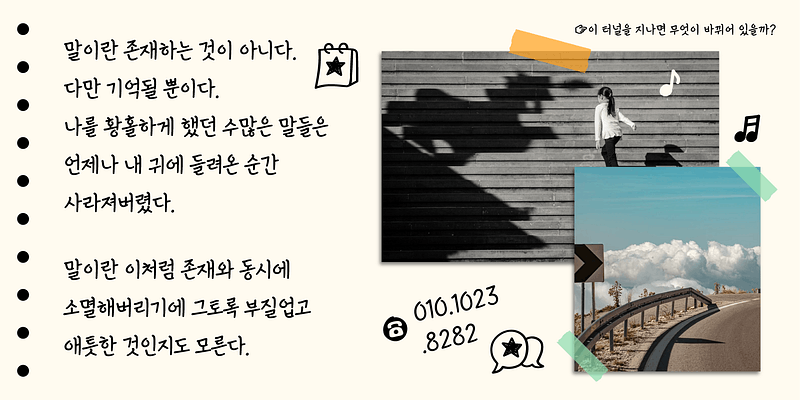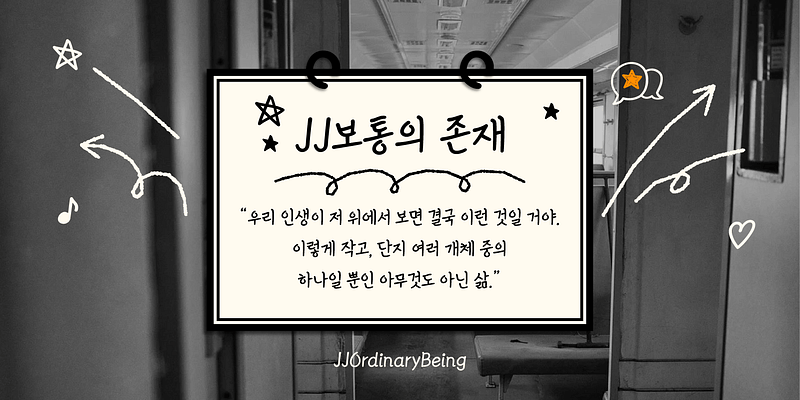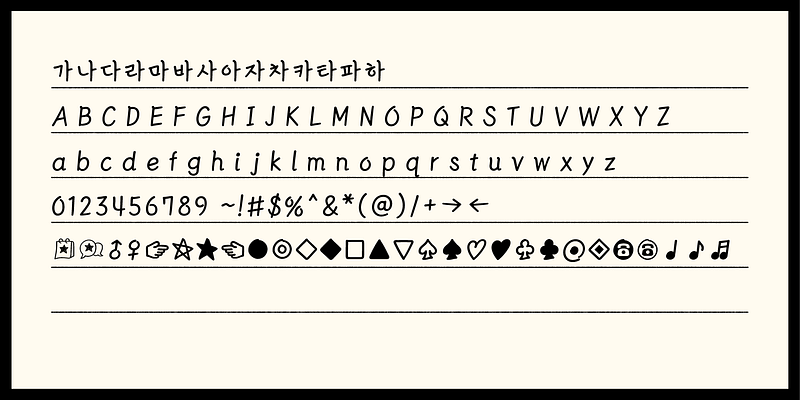
En el vasto universo, la Tierra es como una mota de polvo y nuestras vidas también. El tipo de letra OrdinaryBeing transmite una impresión de seriedad y una inclinación ascendente natural, creada por la sensación de escritura a mano, lo cual le otorga un encanto atractivo.